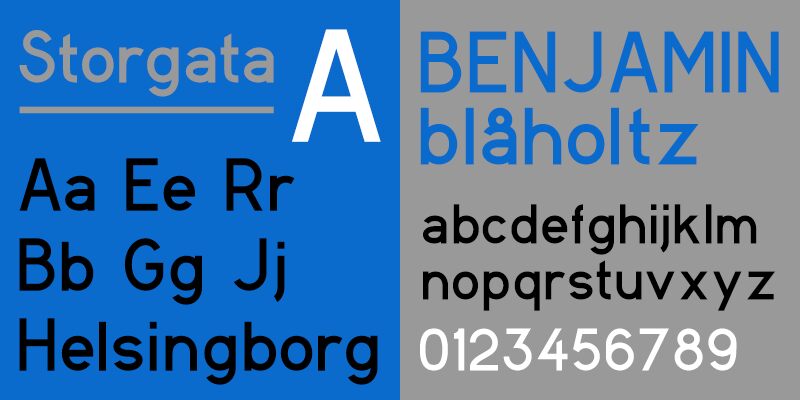
Storgata ist eine meiner ersten professionellen Schriften.
Sie ist stark von Tratex inspiriert, dem Font, der auf schwedischen Verkehrsschildern verwendet wird. Wie ihr Vorbild zielt Storgata auf Neutralität und exzellente Lesbarkeit ab.
Sie enthält eine Vielzahl an Sonderzeichen und Akzenten für umfassende Sprachunterstützung, einschließlich Kyrillisch, Griechisch und mehr.